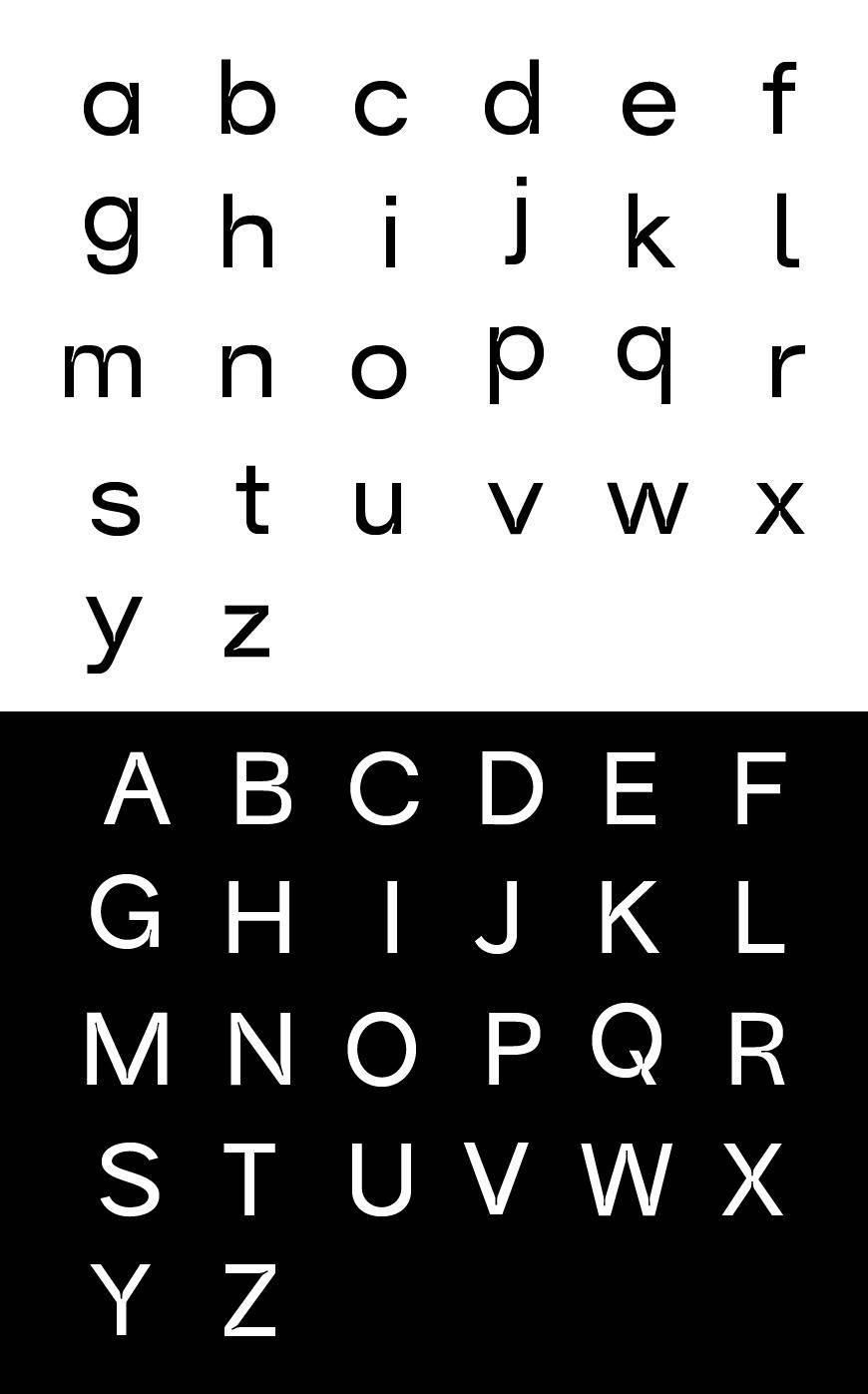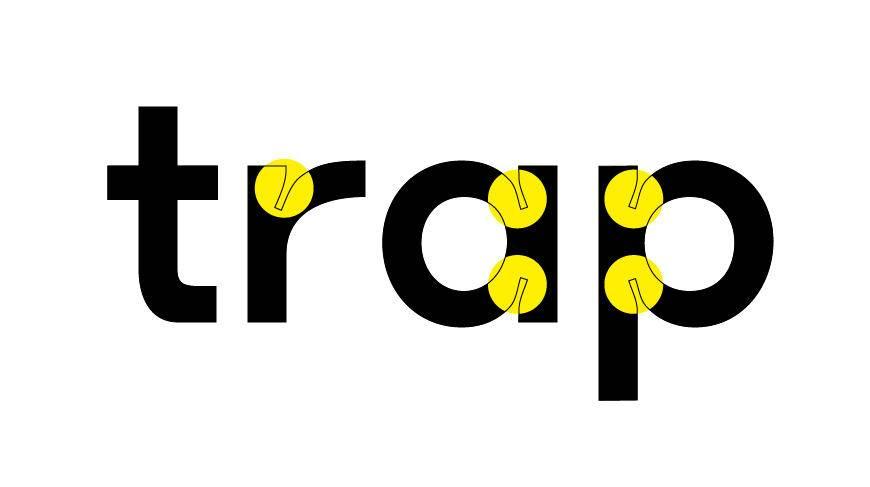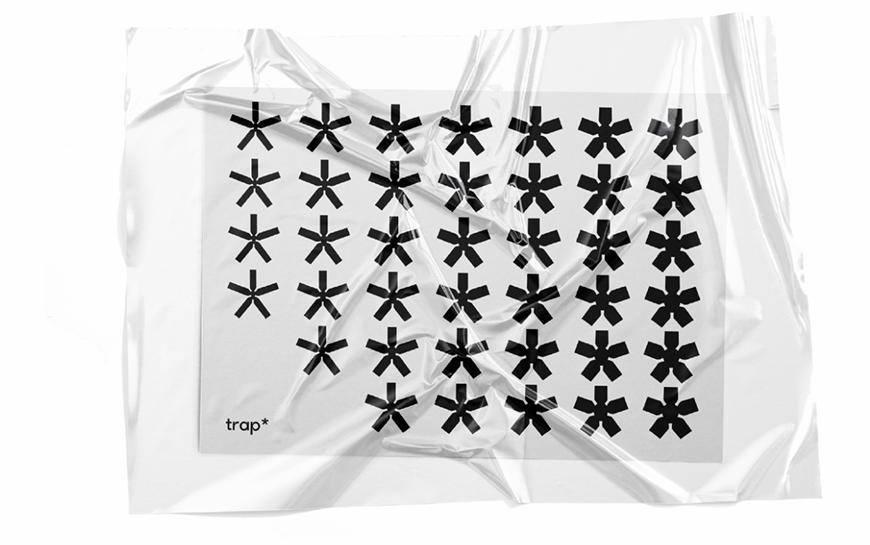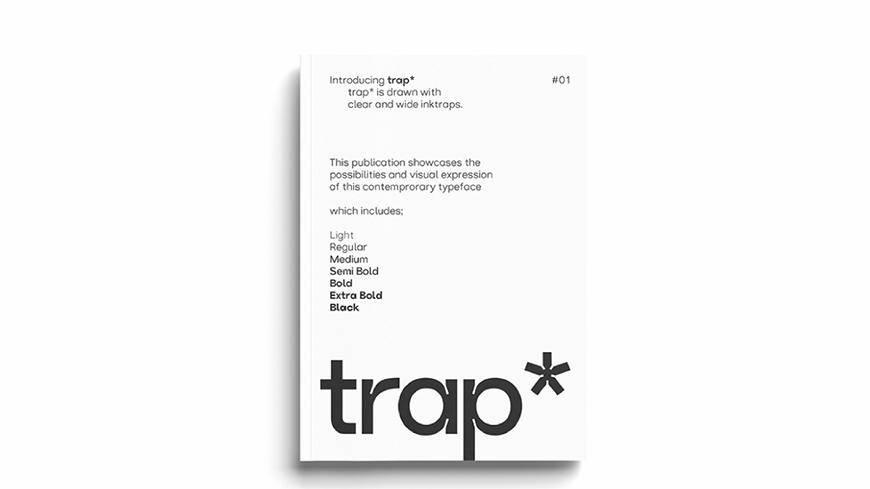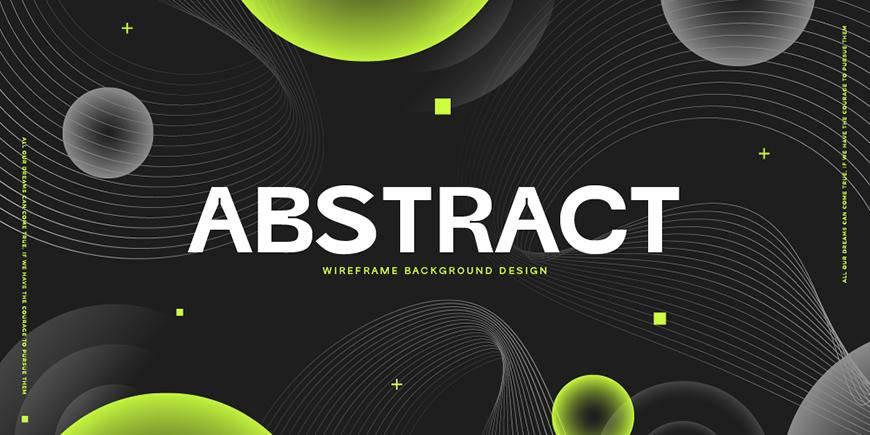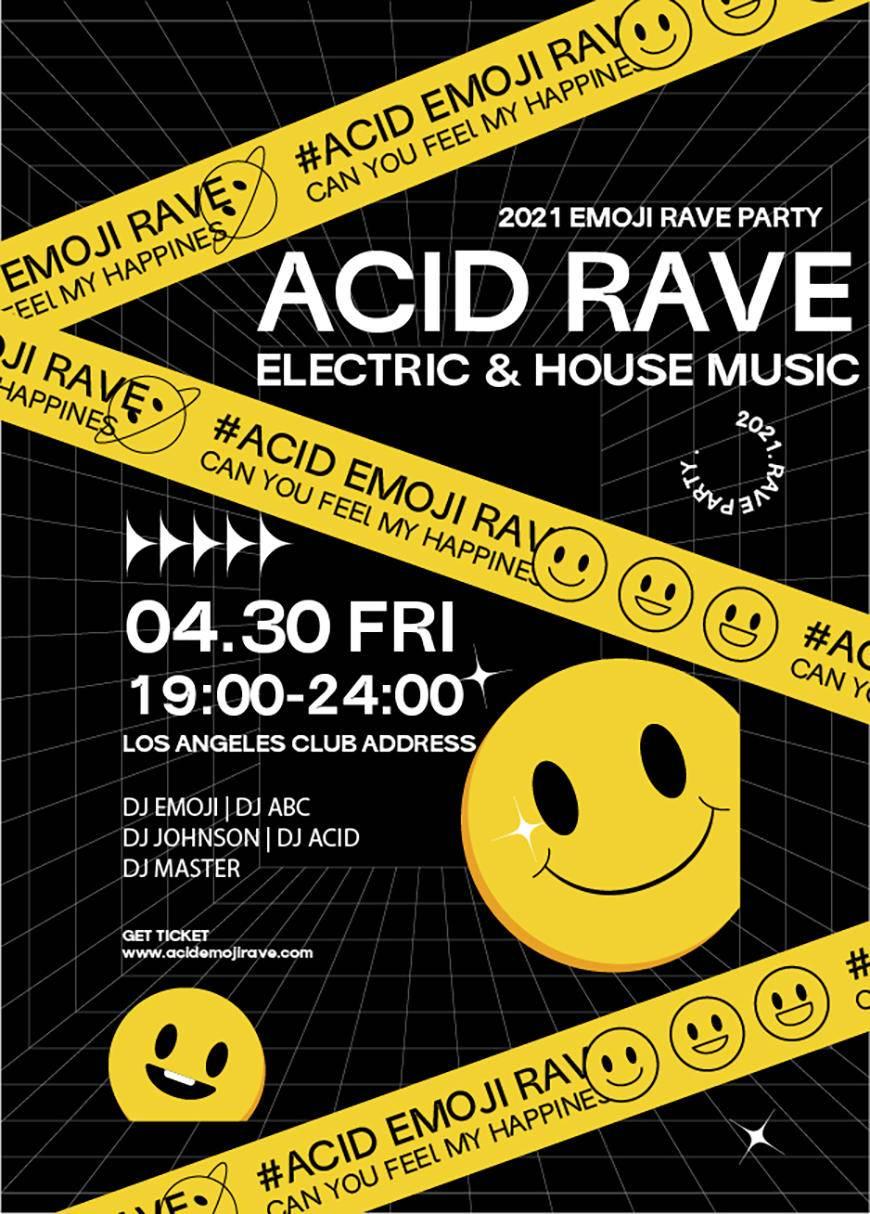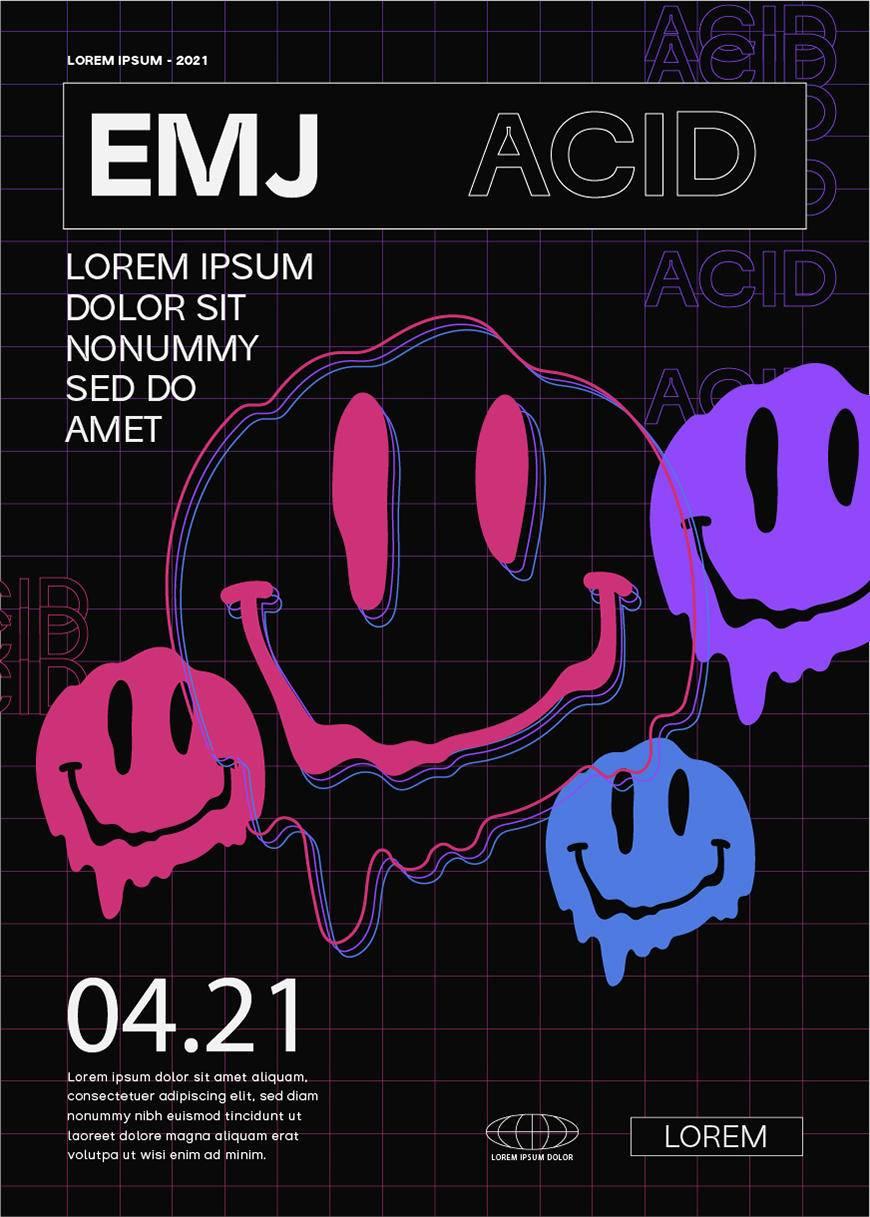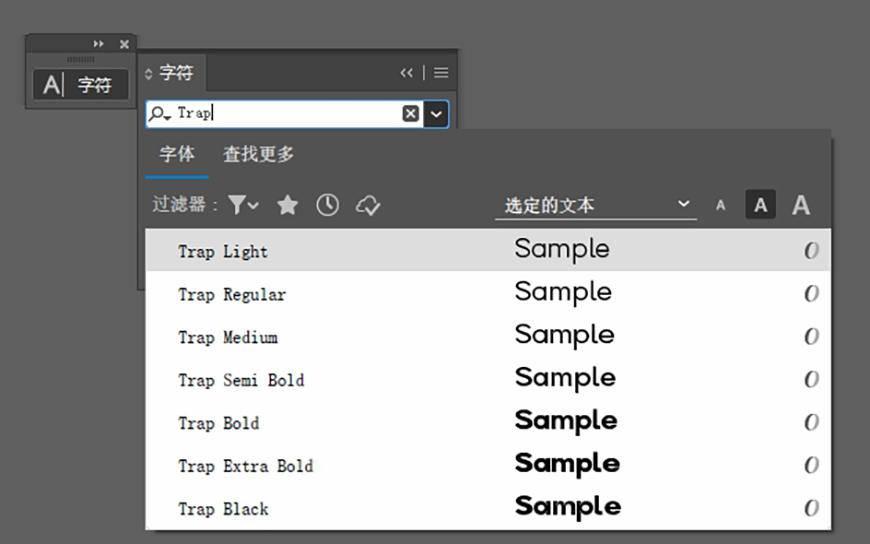
Trap字体下载,在小尺寸印刷依然美观的免费字体
今天发现了一个超棒的字体——Trap*,真的是字体界的宝藏!它是一款现代无衬线英文字体,有 7 个字重,从超细到超粗都能满足,可塑性太强了!还免费商用!
免费字体下载!一款拥有七个字重的现代无衬线英文字体—Trap*
这款字体的设计细节超级赞!笔划连接处有向内延伸的缺口,这种设计在小尺寸印刷时能防止墨色侵入,保持字体轮廓清晰,同时在屏幕上也显得很有设计感。就像在平凡中藏着精致的小巧思,越看越喜欢。
字体特征:
• 字形规则:整体字形比较规则,结构清晰。
• 辨识度高:外形与普通标准字体相差不大,易于识别。
• 细节设计:放大观察可见精心设计的痕迹,笔划连接处有向内延伸的缺口,保持轮廓。
• 屏幕显示效果:这种设计在屏幕上显示时增加了设计感。
• 字重与类型:这款字体拥有7个字重,属于现代免费无衬线字体。
• 小尺寸印刷设计:特别设计了陷印,使字体在小尺寸印刷上更显优雅。